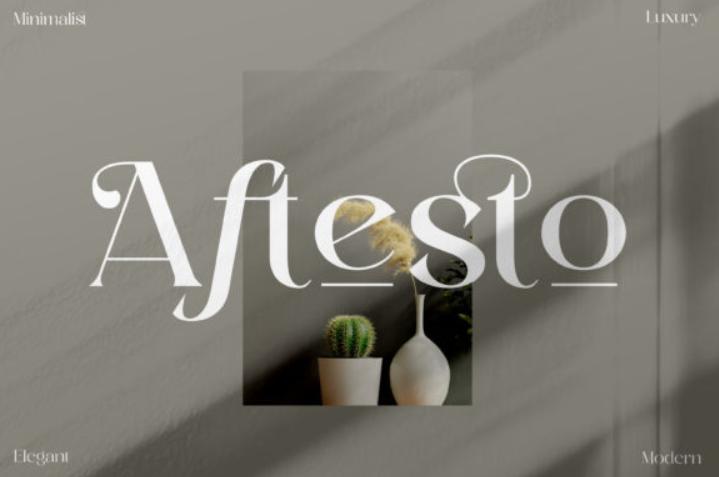
[Creativefabrica] Aftesto Font (storytypestudio)
Aftesto - это элегантный и отчетливый шрифт с засечками. Он закодирован в кодировке PUA, что означает, что вы можете легко получить доступ ко всем глифам и росчеркам! Добавьте его уверенно к своим любимым творениям.